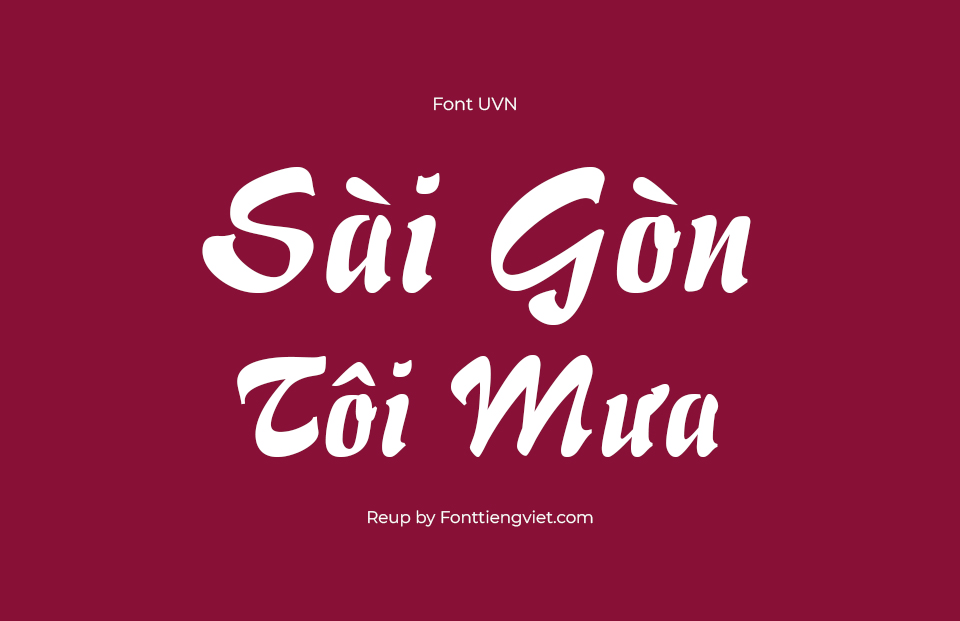
Trong thế giới đồ họa hiện đại, việc tìm kiếm một bộ Font Chữ phù hợp để truyền tải cảm xúc là điều vô cùng quan trọng đối với học sinh và các nhà thiết kế. Font Việt Hóa UVN Bui Doi nổi lên như một lựa chọn độc đáo, mang đậm phong cách đường phố đầy cá tính và sự bụi bặm tự nhiên. Đây là bộ font được tối ưu hóa hoàn toàn cho tiếng Việt, giúp người dùng dễ dàng sử dụng trong các bài thuyết trình, thiệp mời hay các dự án truyền thông học đường mà không lo lỗi hiển thị dấu câu.
Khám phá đặc điểm nổi bật của Font Việt Hóa UVN Bui Doi
Nét vẽ tự do và gần gũi
Đúng như tên gọi, Font Việt Hóa UVN Bui Doi sở hữu những đường nét phóng khoáng, không gò bó theo các quy chuẩn truyền thống. Kiểu chữ này gợi nhắc đến hình ảnh những tấm bảng hiệu vẽ tay cũ kỹ, tạo nên cảm giác gần gũi, mộc mạc và có chút hoài cổ. Điều này đặc biệt phù hợp cho các chủ đề thiết kế mang tính nghệ thuật hoặc cần sự phá cách mạnh mẽ.
Khả năng ứng dụng đa dạng
Dù mang phong cách bụi bặm, font chữ này vẫn đảm bảo được độ dày cần thiết để tạo điểm nhấn thị giác. Bạn có thể sử dụng nó cho các tiêu đề chính trong bìa báo tường, các thiết kế áo lớp hoặc trang trí trang cá nhân. Sự linh hoạt của nó giúp các bạn trẻ thể hiện được cái tôi riêng biệt một cách ấn tượng nhất.